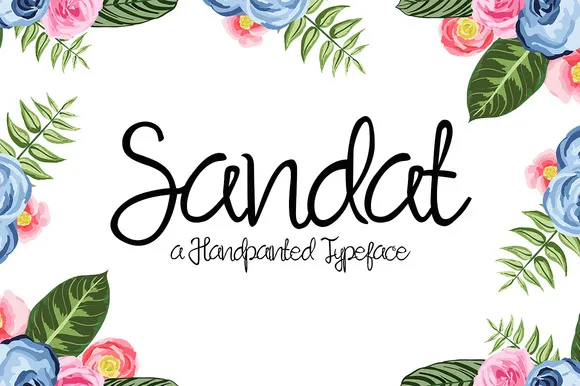
Sandat Script Font – Download Grátis
Introduzimos a Sandat, uma linda fonte script com estilo autoral que adiciona seu toque pessoal ao projeto artístico mais recente. Esta fonte elegante e moderna oferece um olhar refinado aos seus trabalhos de design, criando mensagens únicas e imprimindo uma aura única a qualquer arte ou logotipo. Seja você um designer gráfico profissional ou iniciante, a Sandat se destaca por sua versão escrita à mão, tornando-a perfeita para criações que exigem um toque de personalidade e sofisticação. Composta com precisão em sua forma e linhas, esta fonte vai além dos padrões convencionais, permitindo ao designer uma grande liberdade criativa. Seja você um artista digital ou um ilustrador de arte gráfica, a Sandat está aqui para tornar seus projetos ainda mais especiais. Não perca tempo — invista na sua identidade visual e adquira a Sandat hoje!